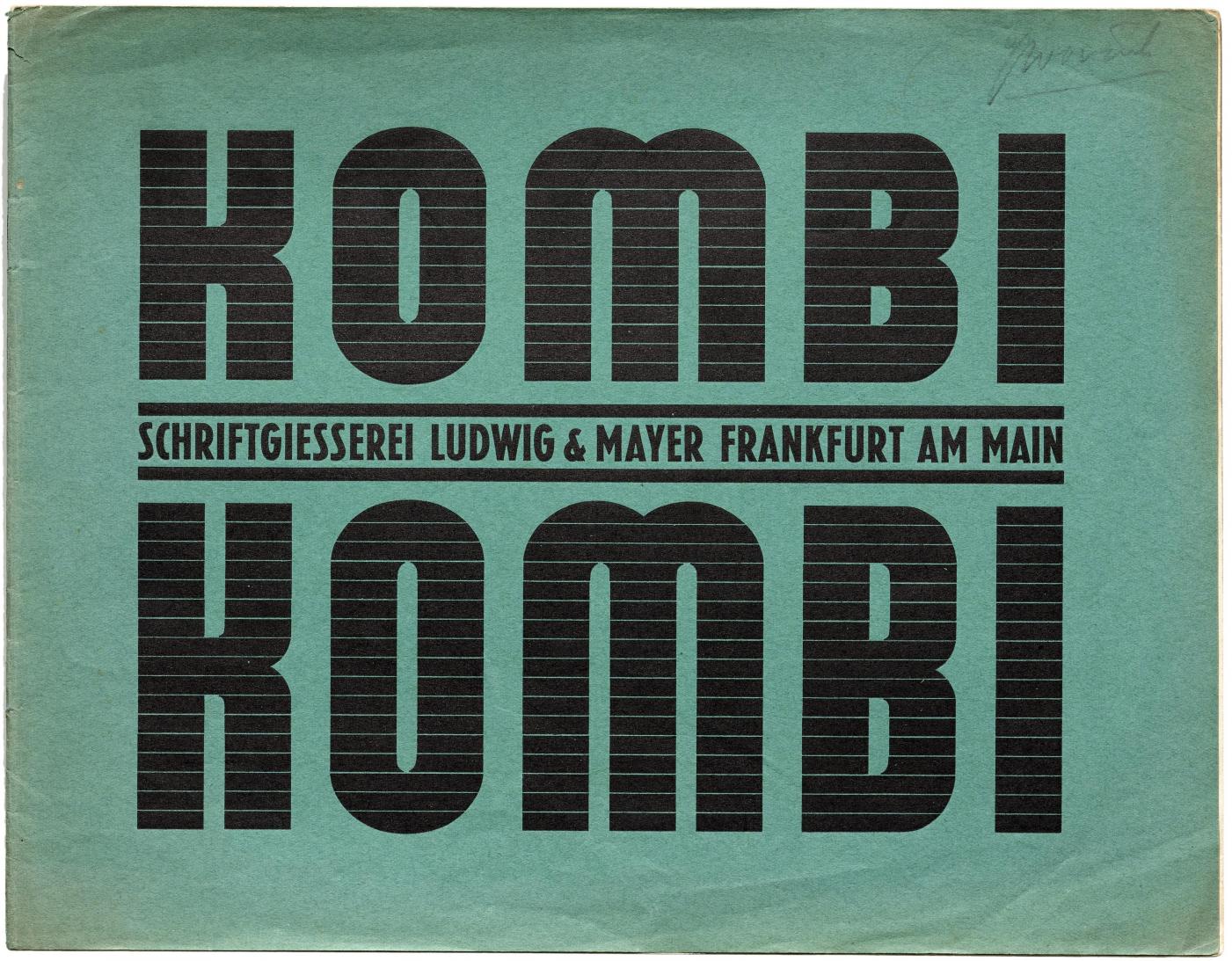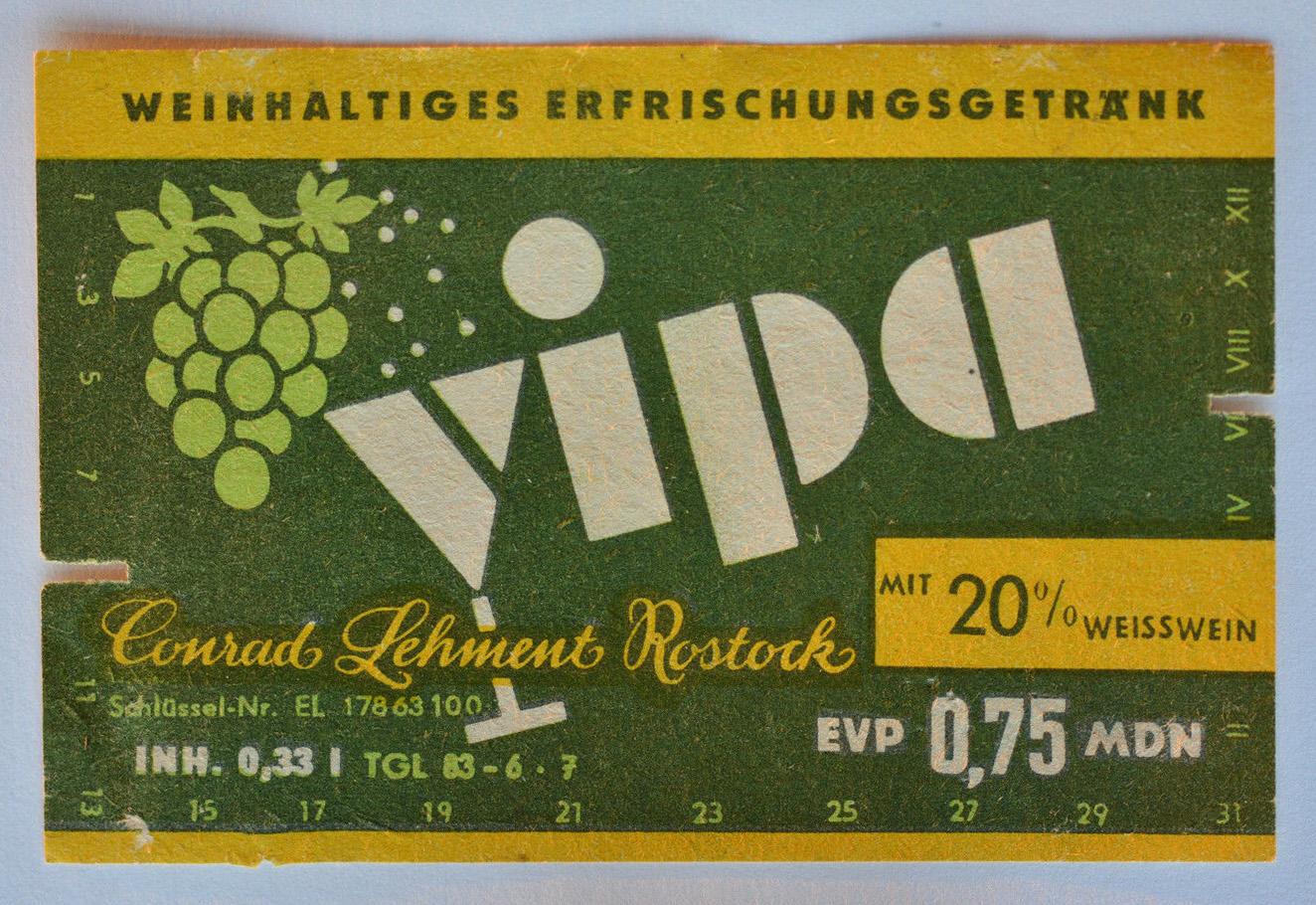
BTW: Die e-r-Kombi bei Anker unten hätte man aber schöner lösen können 8-)
Am schönsten ist der Überfüller bei Conrad Lehment Rostock … :hammer:
Meine Highlights sind das Prozentzeichen und das Ä bei »ERFRISCHUNGSGETRÄNK«.
Was bedeutet „Überfüller“ in diesem Zusammenhang? Und was ist das für eine Währung (MDN)?
(Seit 🇺‍🇸 sind linksgeneigte Schriften – von seltener Landkartenbetrachtung abgesehen – für mich ja ausschließlich Polizeischriften. In diesem Kontext sehe ich sie praktisch täglich, oft mehrmals. 🚓)
Am schönsten daran ist, dass es durch die beispiellose Anstrengung der Werktätigen gelungen ist, neben dem adipösen Überfüller auch noch einen Blitzer zu produzieren. Das nenne ich Planübererfüllung.
Ich fand DDR-Typografie schon toll als es sie noch gab! 1987 hatten wir Klassenfahrt nach Berlin, mit einem Tagesbesuch im Osten. Ich habe damals fleißig Etiketten und Plakate geknipst. Die Fotos sind leider alle futsch.
Ist das, was ich glaube, dass es ist? Eine Schrift, die man selber so weit in der Höhe strecken kann, wie Zwischenstücke verfügbar sind? Genial! :biglove: